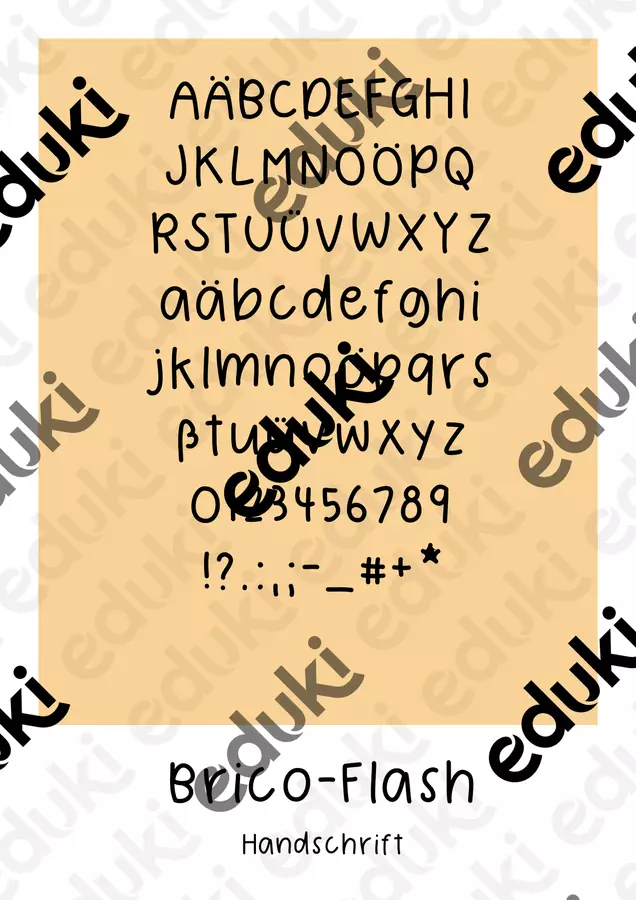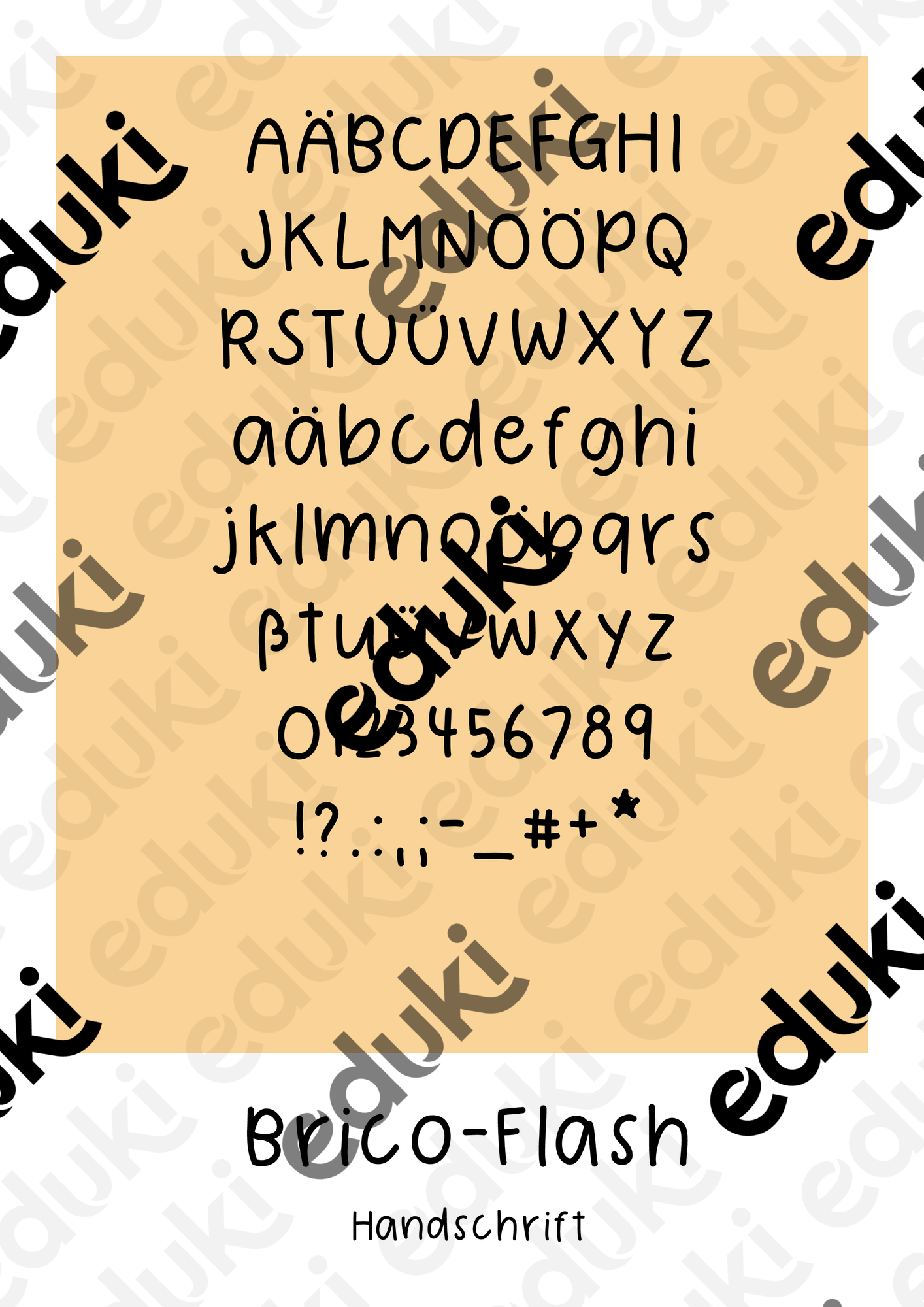
selbst erstellte Schriftarten - Schriftart für dein Arbeitsmaterial - BricoFlash - Bricoliene - Deckblatt
Selbsterstellte Handschrift die sich wunderbar zur Erstellung von Arbeitsblättern oder anderem Unterrichtsmaterial eignet.
Schriftart für dein Arbeitsmaterial - BricoFlash